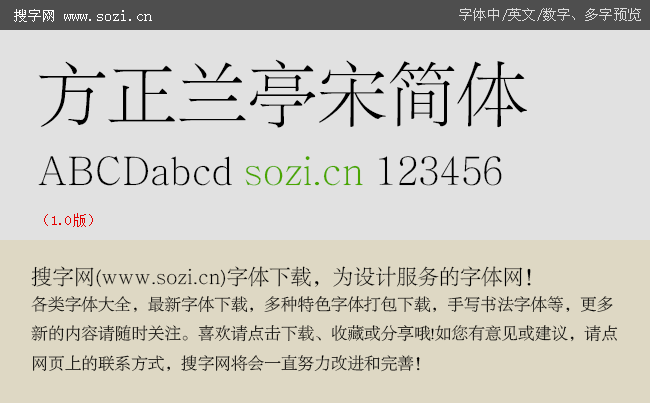
方正蘭亭宋繁體(FZLTSFJ)
搜字網(wǎng)提供一款方正蘭亭宋繁體中文字體下載,方正蘭亭宋是一款字形清秀的中文字體,該字體結(jié)構(gòu)優(yōu)美,識(shí)別性好,常用于產(chǎn)品設(shè)計(jì)、包裝印刷、報(bào)刊雜志、正文標(biāo)題、繪畫(huà)創(chuàng)作等廣告設(shè)計(jì)場(chǎng)合使用。
- 風(fēng)格類(lèi)別: 宋體